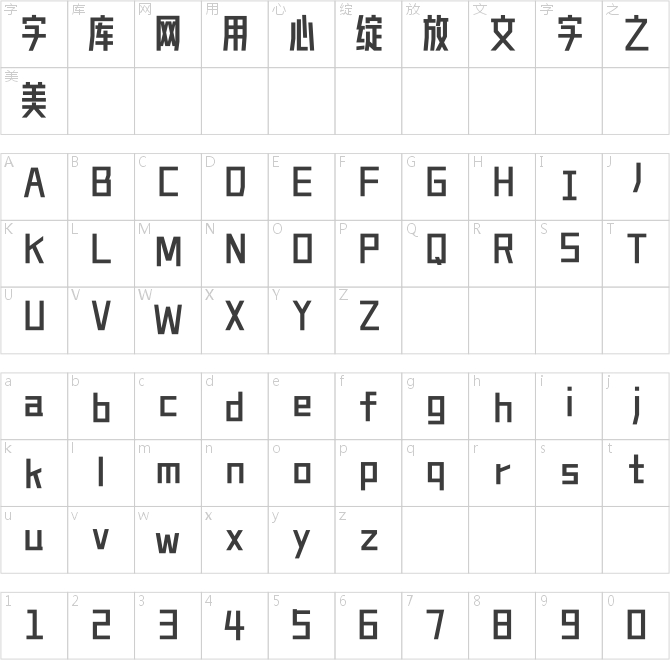
造字工房
造字工房體系列字形修長,瀟灑暢快,給人以通達之感;筆畫縱橫有象,瀟灑淋漓,架構挺拔勁健、布白通透,舒展挺健信然有力,盡顯暢遠通達的律動之美。適用于大標題及個性品牌設計推廣等環境。本字體為簡體字庫,采用OpenType/CID格式,Adobe-GB1-5編碼。基于中華人民共和國GB2312-80字符集標準,另按需添加101個漢字。共收容字數6864CJK漢字,ASCII常用字符100個。